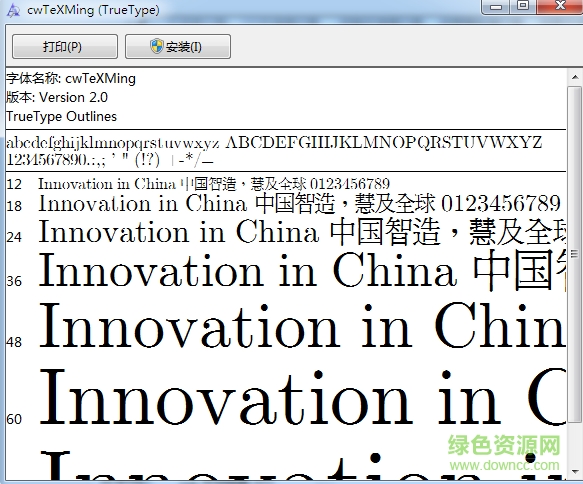
臺(tái)灣明體是一款臺(tái)灣地區(qū)常見的中文字體,這款字體根據(jù)古籍中的字體模仿制作而來,開上去非常的古樸、大方,非常美觀,有需要的朋友歡迎下載使用!
臺(tái)灣明體是一款舊字形外觀,在一定程度上仿照古籍《康熙字典》字體,字形構(gòu)架 穩(wěn)固,莊重而大方,適用於古籍文獻(xiàn)印刷。